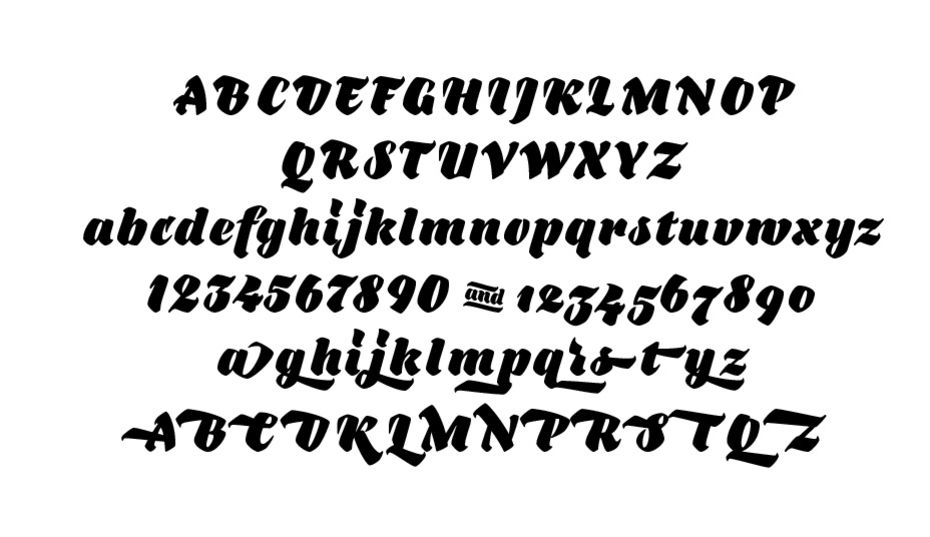
50 лучших свадебных шрифтов: стиль вашей свадебной открытки 2023
Вы ищете лучшие свадебные шрифты чтобы ваша свадебная открытка выглядела красиво и модно? Мы перечислили лучшие шрифты здесь.
Мы знаем, как пугает задача найти лучшие свадебные шрифты. Но вам не о чем беспокоиться, потому что мы позаботились об этом.
На свадьбе есть ряд событий и предметов, которые требуют идеального шрифта. Мы понимаем, что вы не можете выбрать какой-либо свадебный шрифт, потому что вы хотите, чтобы этот день стал самым запоминающимся не только для вас, но и для ваших гостей.
Мы составили список лучшие свадебные шрифты это поможет вам уменьшить ваше бремя.
01 Бургский сценарий
Если мы говорим о лучшем свадебном шрифте, Burgues Script не может не занять первое место в любом списке. Разработанный Алехандро Полом, который известен своим искусством, это, безусловно, самый используемый свадебный шрифт.
02 Афродита Про
Очень легко читаемый шрифт очень важен для свадьбы. Кроме того, это все еще очень крутой и элегантный шрифт, который удивительно красиво смотрятся на свадебной открытке. Его разработали Максимилиано Спровьеро и Сабрина Лопес.
03 Сценарий Конерии
Coneria Script, разработанный Мансом Гребаком, — это тот свадебный шрифт, который придает элегантность, не будучи слишком сложным. Этот шрифт доступен в 3 размерах — легком, среднем и толстом вместе с курсивом.
04 Алекс Браш
Шрифт, который использовали более 4 миллионов пользователей, известен своей смелостью. Идеально наклоненная курсивная поза так приятна для глаз. Ваши повседневные или официальные приглашения будут отлично смотреться с этим шрифтом.
05 Песня ветра
Этот шрифт придаст вам штрих рукописной каллиграфии на вашей пригласительной открытке. Он очень уникален по сравнению со своими конкурентами, и вам не нужно беспокоиться о проблеме читабельности.
06 дело
Другой красивый рукописный шрифт из плейлиста Алехандро Пола, огромный вид Affair завораживает всех. Дополнительные изгибы каллиграфии, наряду со смелым характером, идеально подходят для свадеб.
07 Riesling
Мы все помним мелкий шрифт фильма «Великий Гэтсби», верно? Этот шрифт идеально подходит для темы, вдохновленной Гэтсби. Тощие и круглые персонажи приобретут тот винтажный вид, которого вы так жаждали.
08 Алина
Этот шрифт, разработанный Микой Мелваш, подходит не только для свадебных приглашений, но и для создания логотипов.
Шрифт выглядит таким живым и смелым, в то же время он также приятен для глаз.
09 Mishka
Модель Mishka, идеально подходящая для того, чтобы привлечь всеобщее внимание, была разработана Эмилем Бертеллом в 2011 году. Изогнутые детали будут красиво смотреться на пригласительном билете. Вам не нужно много думать об этом шрифте при выборе.
10 Барочный сценарий
Если вы хотите дать гостям почувствовать, что церемония будет такой же захватывающей, как и шрифт, Baroque Script идеально подойдет. Каллиграфия и смелый характер легко читаются.
11 Каролина Блэк
Основатель Эмили Лайм и дизайн Эмили Коннерс, Кэролайн Блэк идеально подходит для написания имени пары. Этот шрифт имеет кривые для правильных символов и алфавитов.
12 Сценарий Бикхэма
Еще один шедевр семейства Adobe, Bickham Script, был вдохновлен мастерами письма 18 века. Этот шрифт идеально подходит для настроек дисплея и иллюстрирует роскошный стиль.
13 соответственный
Расширенная кривая символов — вот что делает Respective одним из лучших свадебных шрифтов.
Он был разработан Мансом Гребахом. Он доступен в 2 размерах шрифта — обычном и росчерках.
14 Адиос Скрипт
Нам не хватает шрифтов, разработанных Алехандро Полом, и этот — еще один шедевр из его ведра. Этот шрифт будет иметь романтическое влияние на ваши свадебные приглашения.
15 Дышать
Этот стильный шрифт создает впечатление игры с кривыми. Breathe был разработан Максимилиано Р. Спровьеро в 2010 году. Это сочетание смелости и роскоши.
16 Передний h2
Мы понимаем, что некоторые из вас могут захотеть, чтобы приглашение было во всех столицах, и мы предоставили вам Frente h2. Тонкий блочный почерк может идеально подойти для вашего уникального приглашения.
17 Большие Vibes
Будь то официальная свадьба или повседневная, как следует из названия, шрифт подарит своим читателям отличное настроение. Элегантный заглавный шрифт как вишенка на торте.
18 Свеча
Ищете шрифт, который придаст вашему приглашению профессиональный, но привлекательный вид? Candlescript может быть идеальным свадебным шрифтом в этом сегменте.